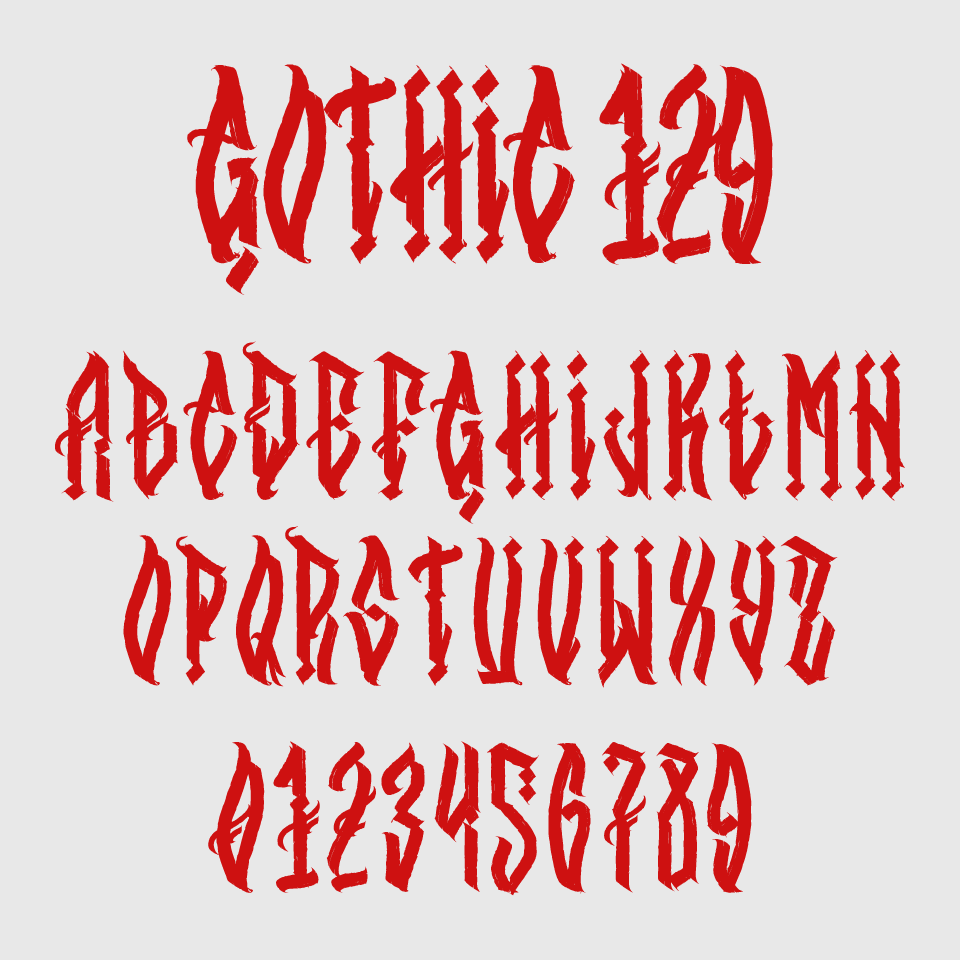
Gothic 129フォントは、鋭角的で密度の高いラインが特徴的な、ハードコアな手書き風のゴシックフォントです。
荒々しいシャープな筆致により、攻撃的でエッジの効いた印象を放ち、視覚的にかなりの存在感を感じさせるかっこいいデザインです。
ブラックメタルやホラー系、ストリートカルチャーをモチーフにしたデザインに適しており、ダークで混沌とした世界観の演出にぴったりです。読みやすさは控えめですが、その分グラフィック的な力強さで強烈な印象を残すフォントです。